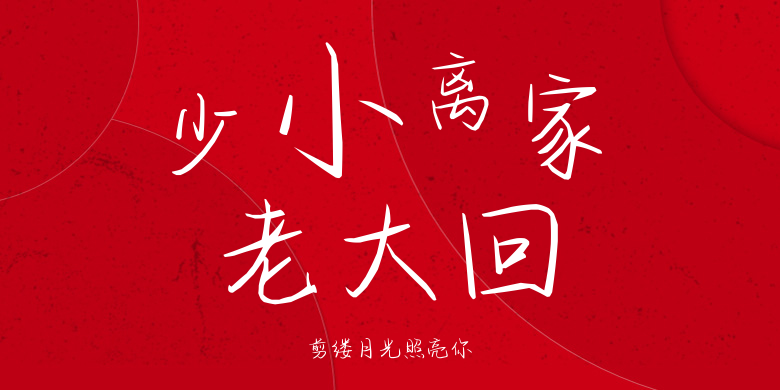
剪缕月光照亮你
剪缕月光照亮你,这款字体结构工整、笔画清晰,兼顾美观与易读性,适用于标题、正文、海报、包装、LOGO 等多种场景。字形优雅稳定,风格百搭耐看,适配日常排版与创意设计,让文字呈现更舒适、更具质感。剪缕月光照亮你一笔一画,皆是细节,以均衡的比例、流畅的线条打造舒适视觉体验,字形端正大气,风格简约现代。无论是商业设计、品牌宣传还是日常排版,都能轻松驾驭,让文字更有格调与力量。剪缕月光照亮你字体下载。